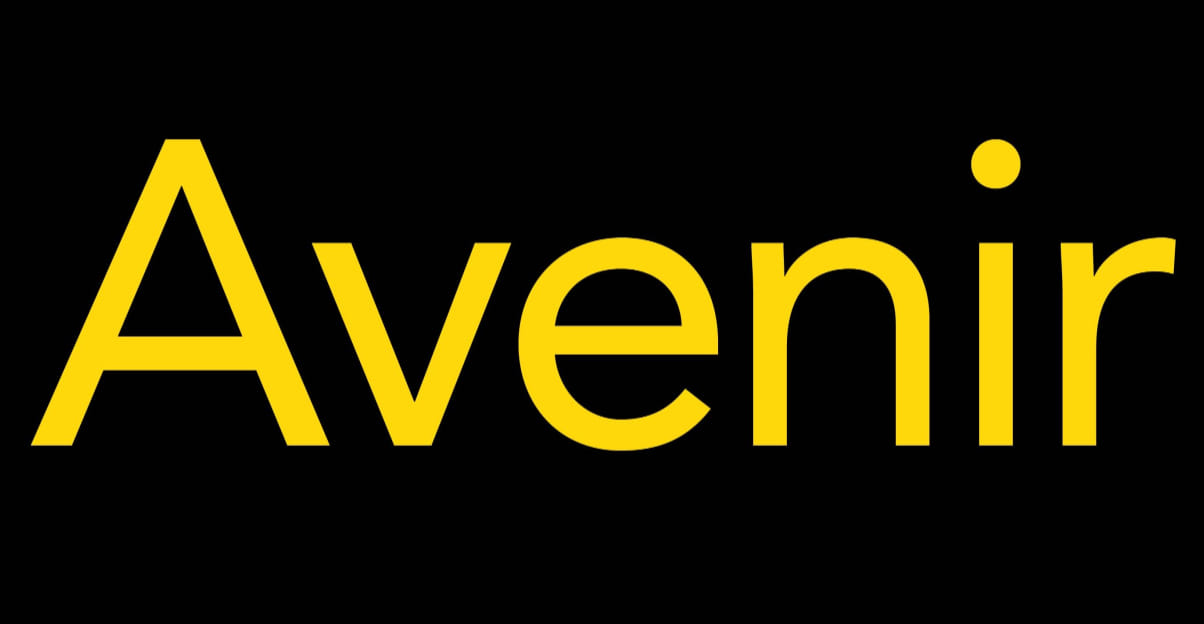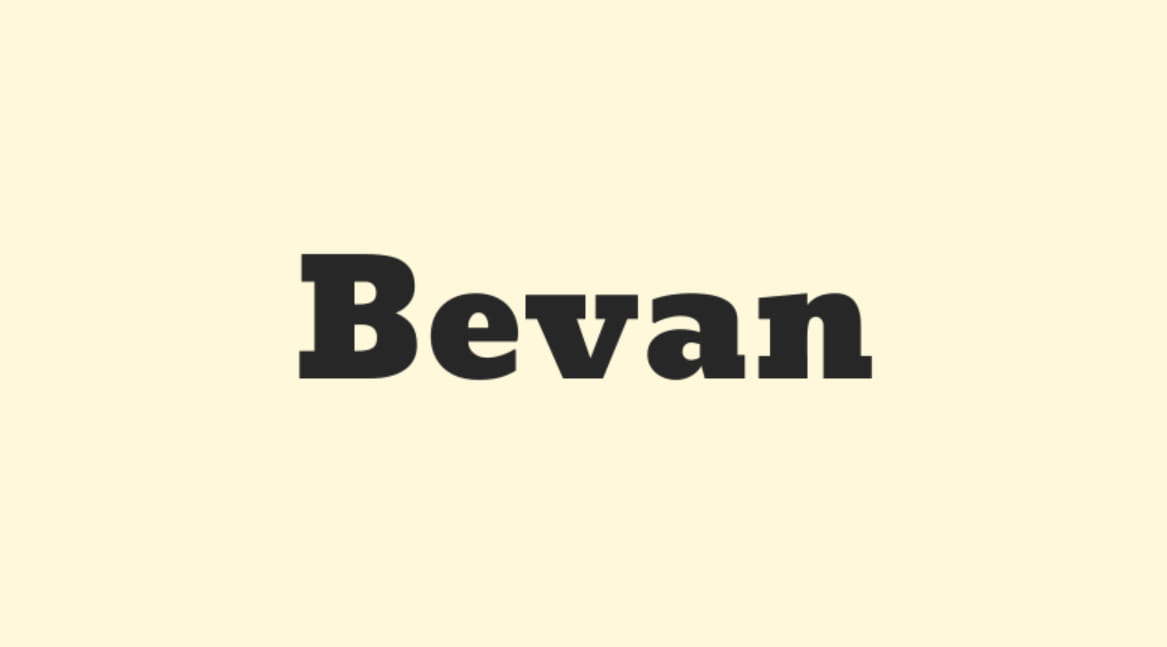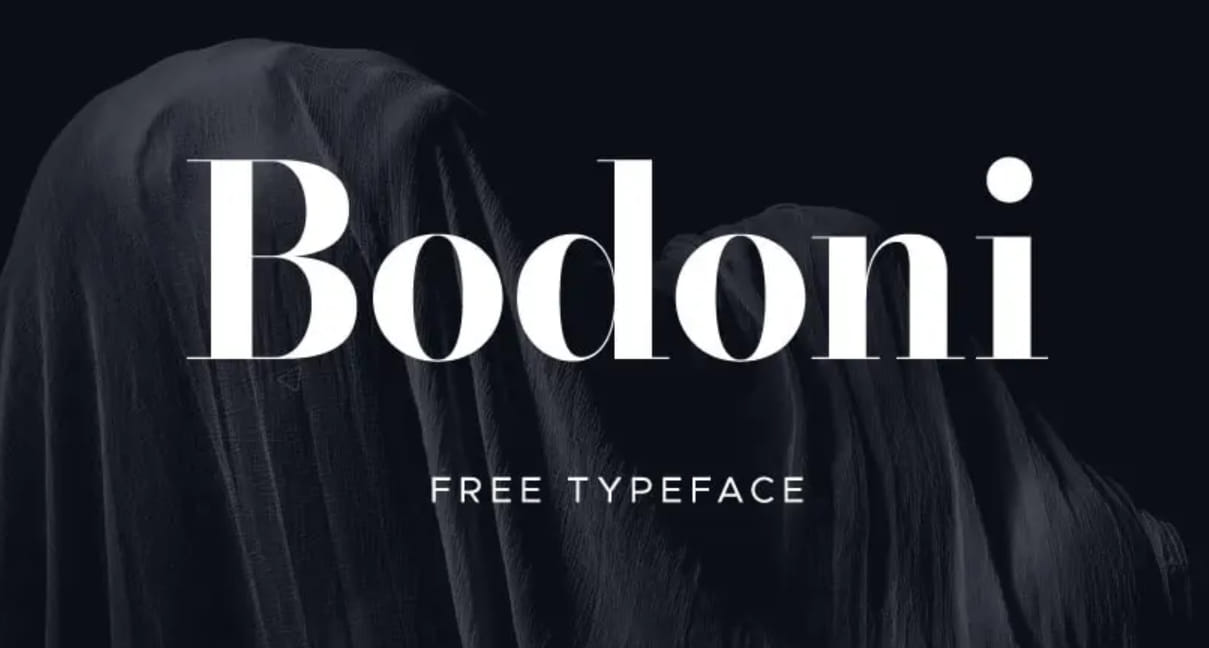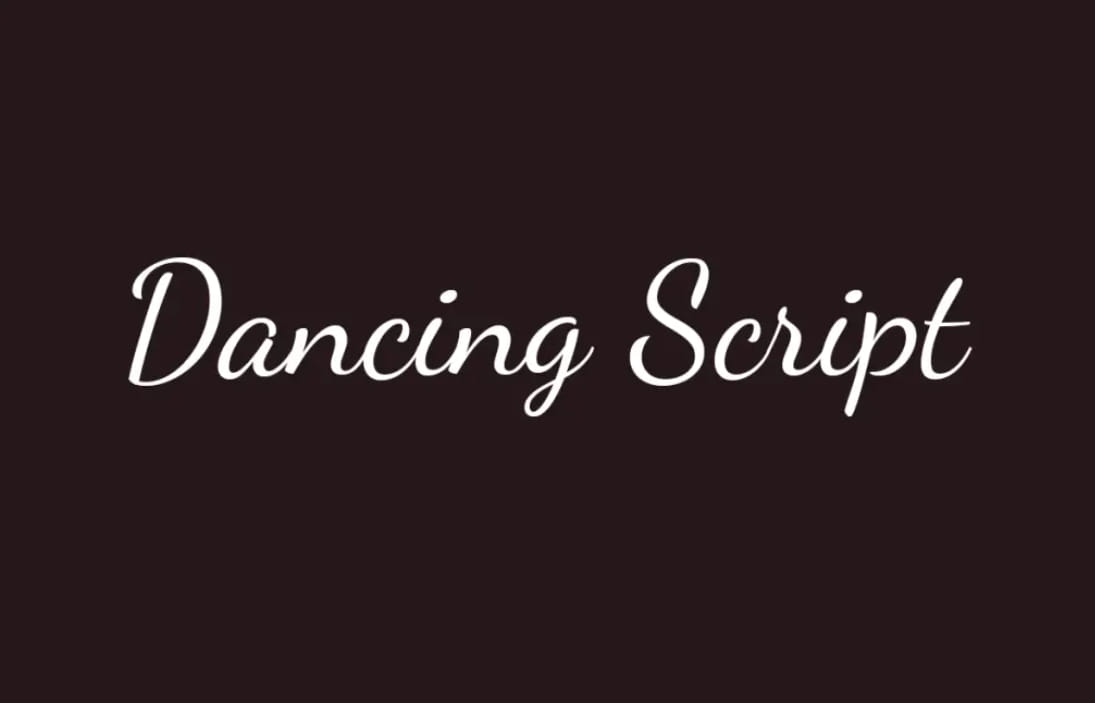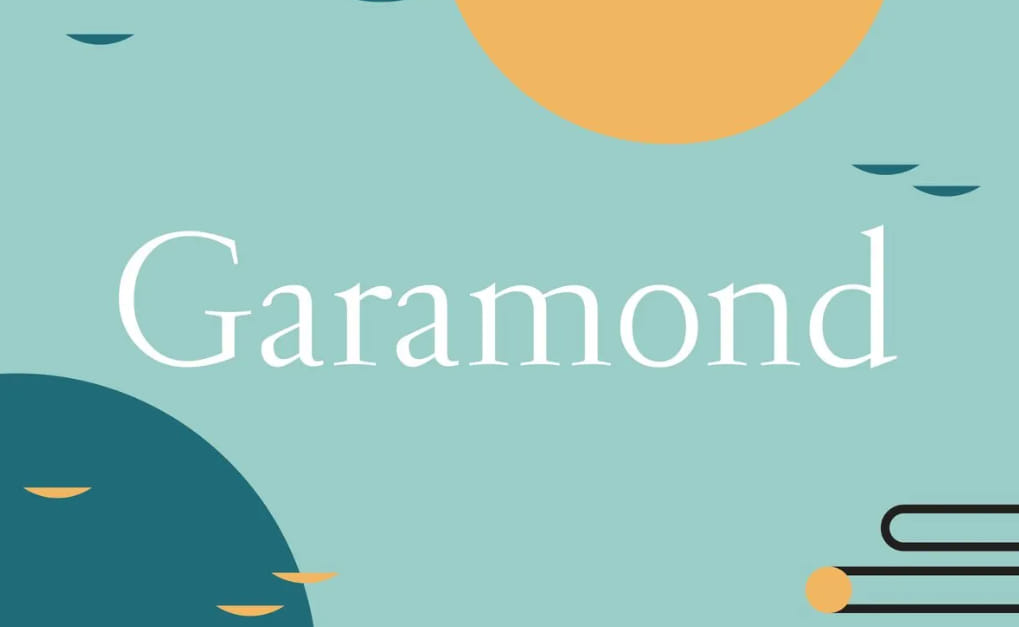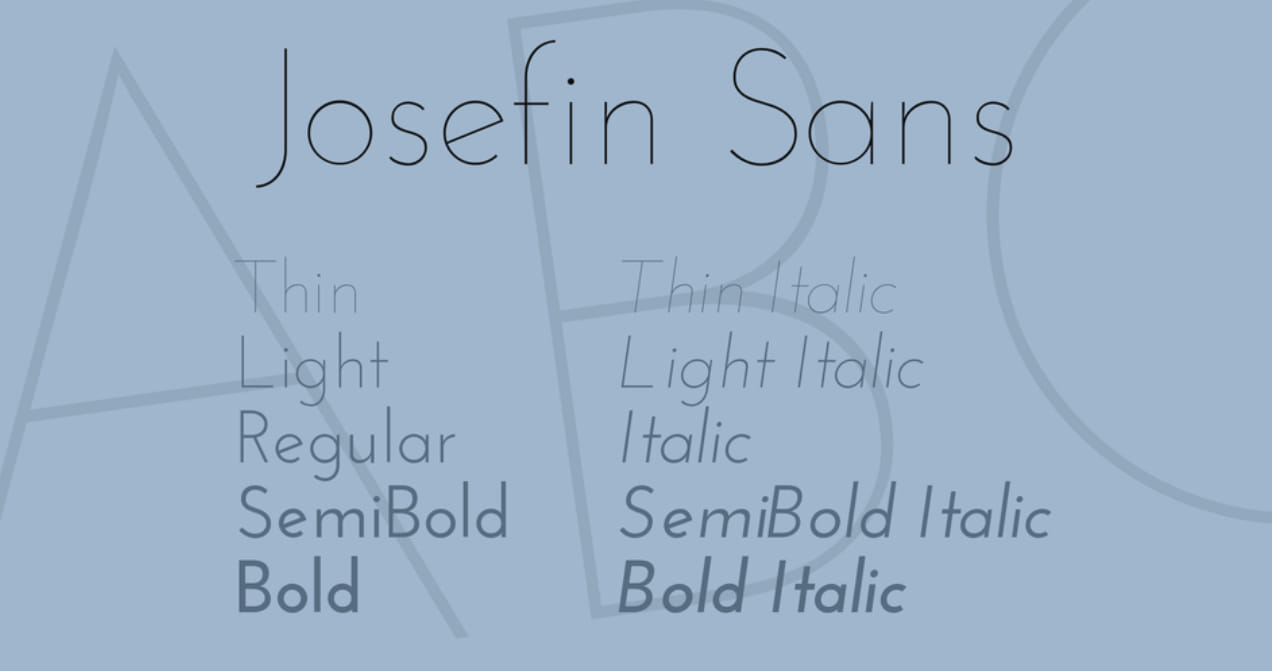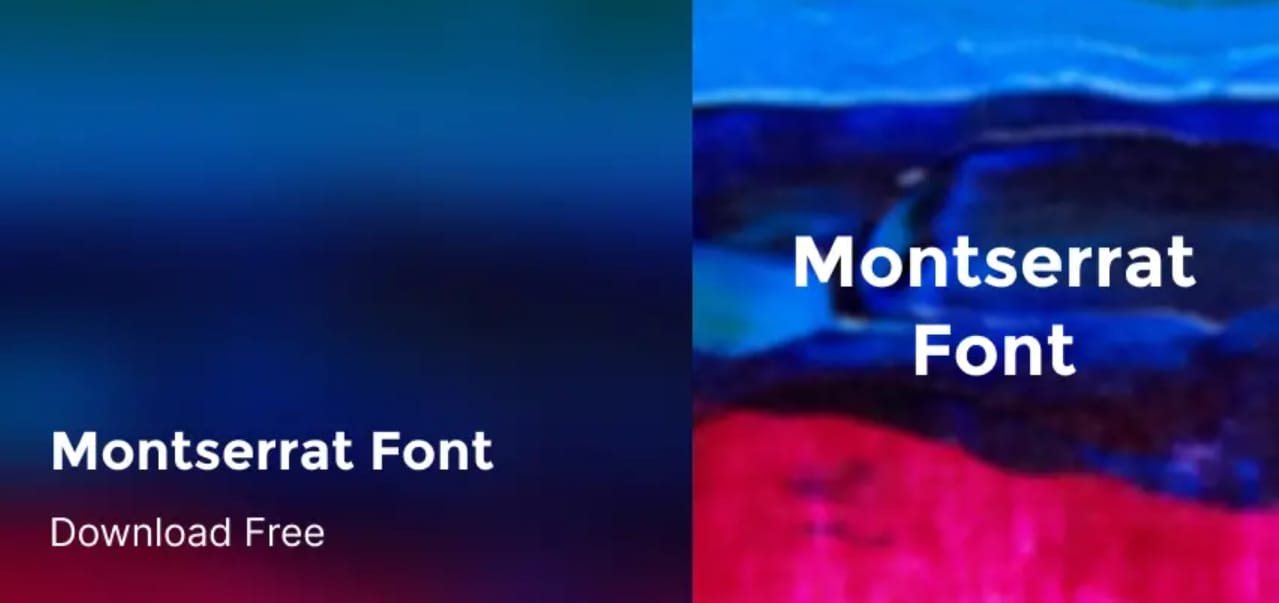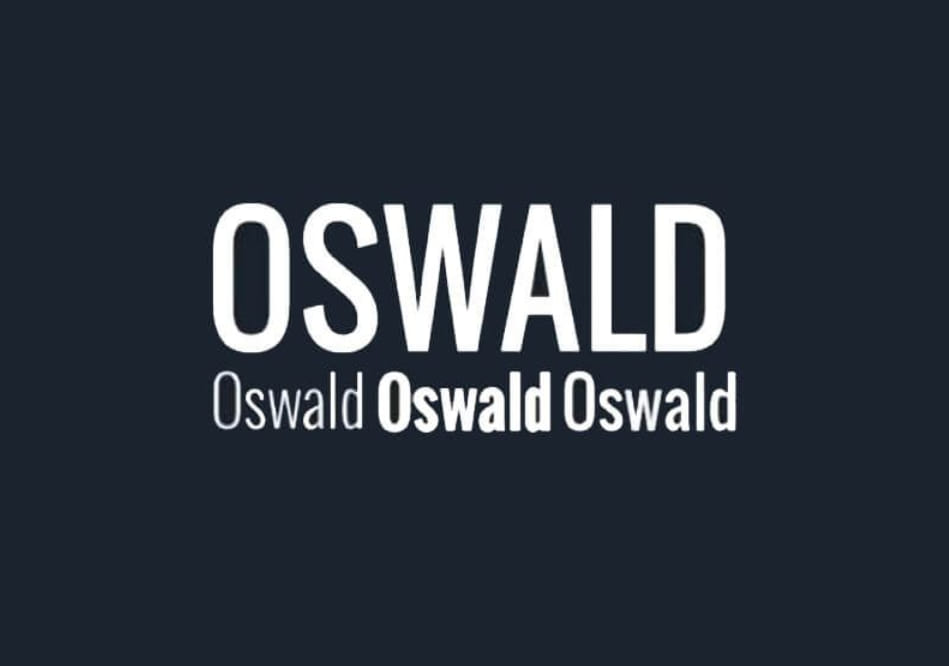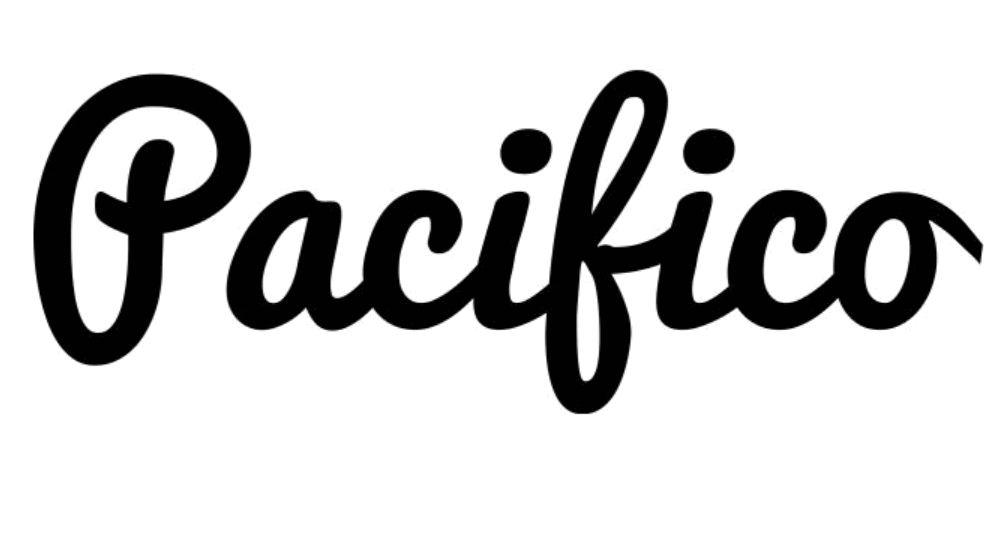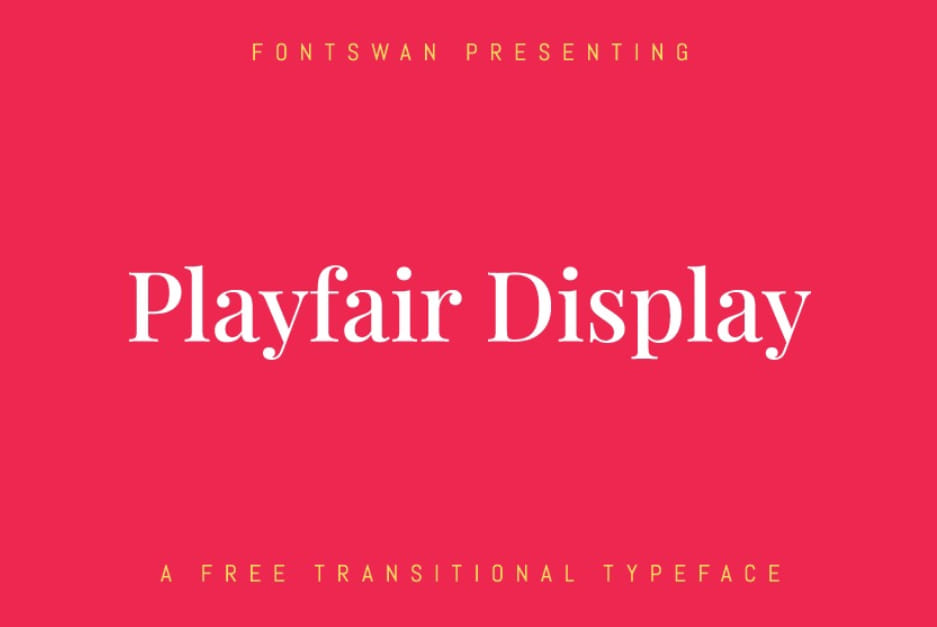
17 Nama Font Aesthetic yang Membuat Desain Anda Tampil Menawan
Dalam dunia desain, pemilihan font tidak hanya tentang legibilitas, tetapi juga tentang estetika. Font yang tepat dapat meningkatkan daya tarik visual dan menciptakan suasana yang diinginkan.
Berikut adalah 17 font aesthetic yang dapat Anda pertimbangkan untuk proyek desain Anda:
1. Helvetica Neue
Yang pertama adalah Helvetica Neue. Font ini dibuat oleh Max Miedinger dan Eduard Hoffmann, Helvetica Neue adalah penyempurnaan dari font Helvetica klasik. Dengan garis yang bersih dan modern, font ini sering digunakan dalam branding korporat dan desain grafis.
2. Futura
Font Futura dirancang oleh seorang designer yang bernama Paul Renner. Futura adalah font geometris sans-serif yang mencerminkan estetika Bauhaus. Dengan bentuknya yang sederhana dan elegan, Futura banyak digunakan dalam judul dan logo.
3. Garamond
Garamond, terutama untuk versi yang dibuat oleh Claude Garamond, adalah font serif yang bertema klasik. Dengan sentuhan elegan dan tradisional, Garamond sering dipilih untuk penerbitan buku dan materi cetak.
4. Bodoni
Font Bodoni dibuat oleh Giambattista Bodoni, font ini memiliki kontras yang tajam antara garis tebal dan tipis. Bodoni memberikan kesan mewah dan elegan, sering dipakai dalam majalah mode dan branding mewah.
5. Montserrat
Montserrat adalah font sans-serif yang terinspirasi dari tanda-tanda jalan di lingkungan Montserrat di Buenos Aires. Desainnya yang modern dan bersih membuatnya cocok untuk web dan desain UI.
6. Playfair Display
Playfair Display adalah font serif dengan sentuhan modern. Dengan gaya yang cocok untuk judul dan display, font ini sering digunakan dalam majalah dan situs web fashion.
7. Raleway
Raleway adalah font sans-serif elegan dengan garis yang halus. Sangat cocok untuk desain minimalis dan konten digital yang bersih.
8. Lobster
Lobster adalah font script yang playfull dan dinamis. Dengan sentuhan artistik, font ini cocok untuk desain kreatif dan kasual.
9. Pacifico
Selanjutnya ada font Pacifico. Font ini adalah font script yang terinspirasi dari gaya tulisan tangan Amerika 1950-an. Dengan sentuhan retro, Pacifico bagus untuk desain yang ingin menampilkan kesan vintage.
10. Bevan
Bevan adalah reinterpretasi dari font serif klasik, memberikan kesan yang kuat dan tegas. Cocok untuk judul dan tampilan yang membutuhkan dampak visual.
11. Avenir
Dirancang oleh Adrian Frutiger, Avenir adalah font sans-serif dengan nuansa geometris. Avenir sering digunakan dalam desain korporat dan UI karena legibilitasnya yang tinggi.
12. Josefin Sans
Josefin Sans menawarkan gaya geometric sans-serif dengan sentuhan vintage. Sangat cocok untuk desain yang ingin menciptakan suasana retro-modern.
13. Slabo 27px/13px
Slabo adalah font serif khusus yang dirancang untuk tampilan web, tersedia dalam dua ukuran: 27px dan 13px. Font ini memberikan konsistensi visual yang bagus untuk konten digital.
14. Roboto
Roboto adalah font sans-serif yang dirancang oleh Google. Dengan gaya yang netral namun ramah, Roboto sering digunakan dalam desain UI dan UX.
15. Oswald
Oswald merupakan font jenis sans-serif yang dioptimalkan untuk tampilan layar. Dengan gaya yang lebih ketat dan bersih, Oswald cocok untuk judul dan konten online.
16. Dancing Script
Dancing Script merupakan font script yang ringan dan bersemangat. Dengan garis yang bergerak bebas, font ini memberikan sentuhan personal dan ramah.
17. Lato
Lato adalah font sans-serif yang dirancang oleh Łukasz Dziedzic. Dikenal karena keserbagunaannya, Lato menggabungkan kesederhanaan dengan karakteristik yang hangat dan ramah, menjadikannya ideal untuk berbagai keperluan, mulai dari konten web hingga materi pemasaran.
Penutup
Menggunakan font yang tepat dapat benar-benar mengubah nuansa dan efektivitas desain Anda. Setiap font memiliki karakter dan keunikan yang dapat memperkuat pesan visual yang ingin Anda sampaikan.
Dari elegan dan klasik hingga modern dan dinamis, pilihan font aesthetic dapat membantu Anda menciptakan tampilan yang sesuai dengan tujuan desain Anda.
Eksperimen dengan font-font ini untuk menemukan yang paling cocok dengan proyek Anda, dan saksikan bagaimana mereka dapat mengubah desain Anda dari biasa menjadi luar biasa.